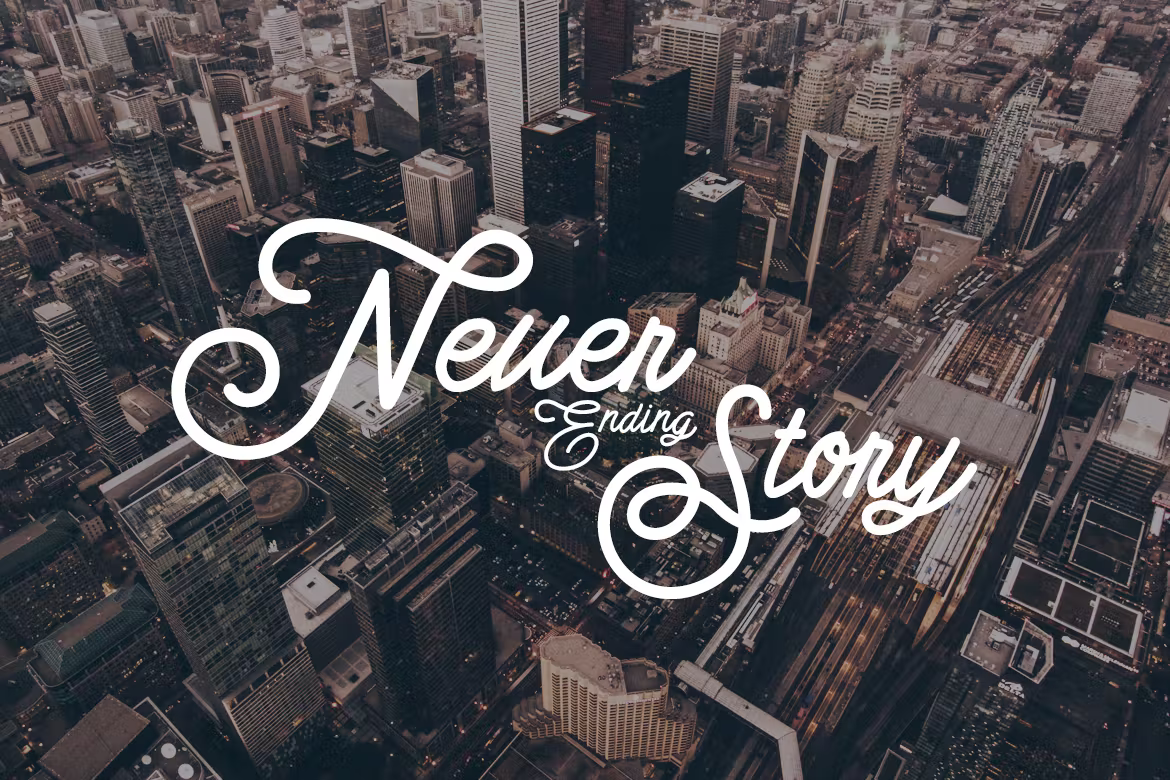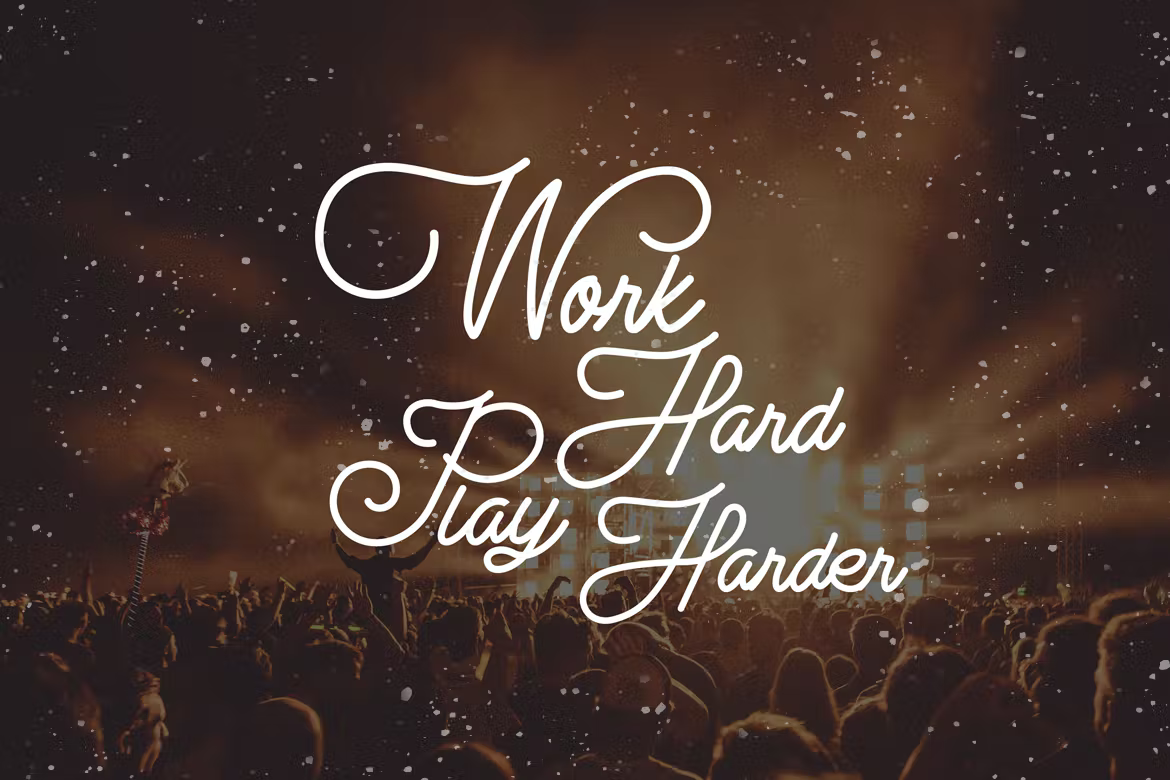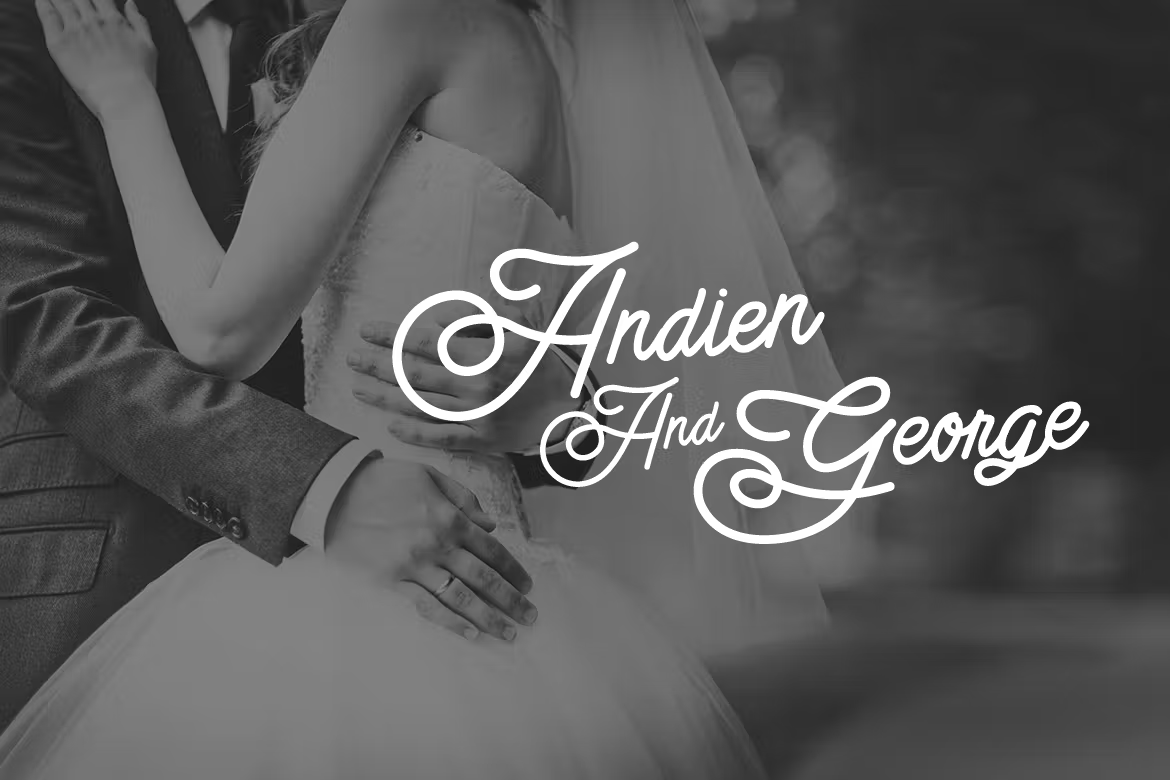
Foundry font pack
Description de Foundry font pack
Nous vous fournissons l’un des meilleurs scripts manuscrits élégants. Meilleure correspondance pour les logos, les en-têtes, les titres, les impressions et autres possibilités de processus créatifs.
Créez des résultats de typographie/lettrage extraordinaires à l’aide de Foundry Font Pack